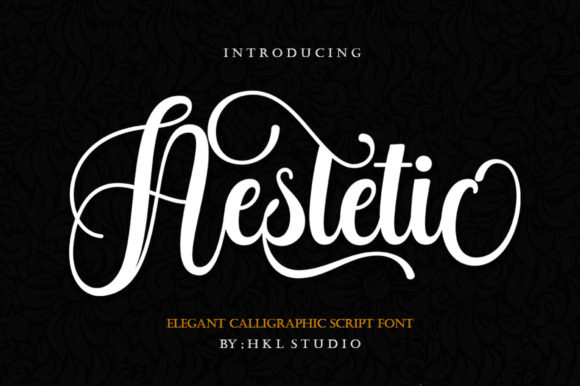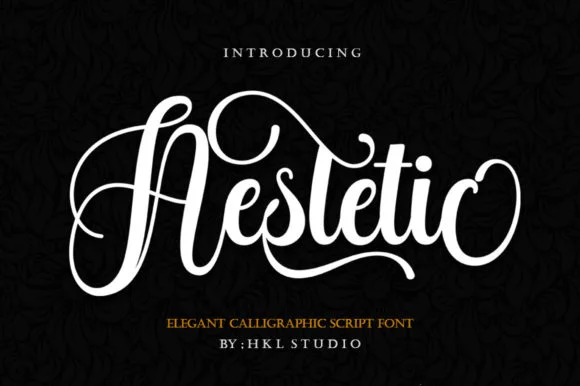
Название: Aestetic Font (2021)
Aestetic - это ослепительный и очень детализированный шрифт.
Независимо от темы, этот шрифт станет прекрасным активом в вашей библиотеке шрифтов, поскольку он способен улучшить любое творение.